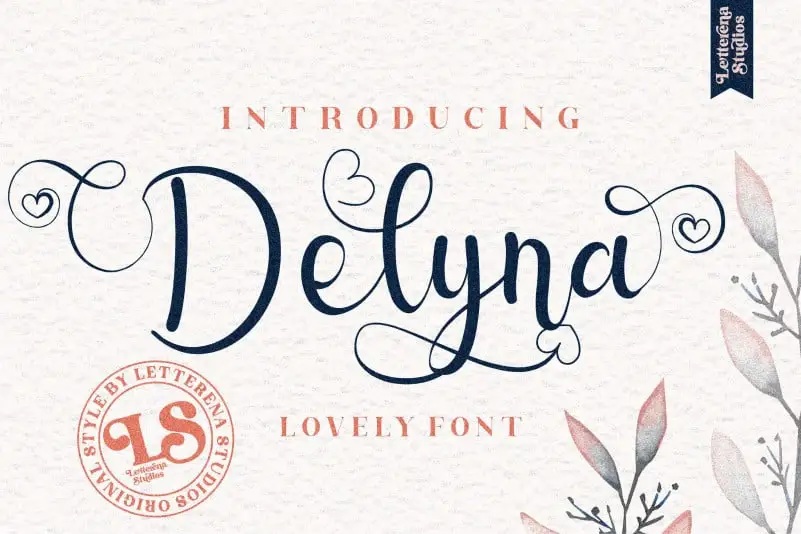
Delyna Calligraphy Font é uma elegante fala à mão que se destaca por seus delicados corações ornamentos. Perfeita para as cartas de aniversário e qualquer outra design pedindo um toque doce, Delyna oferece um toque romântico e encantador. Como fonte PUA (Personal Use Allowed), você pode acessar todos os caracteres e apóstrofos sem nenhuma dificuldade, tornando o processo de criação mais fluido e divertido. Ideal para quem busca uma fonte que adorne seus designs com um toque suave e único, Delyna é a escolha perfeita para qualquer projeto que exija delicadeza e romantismo.